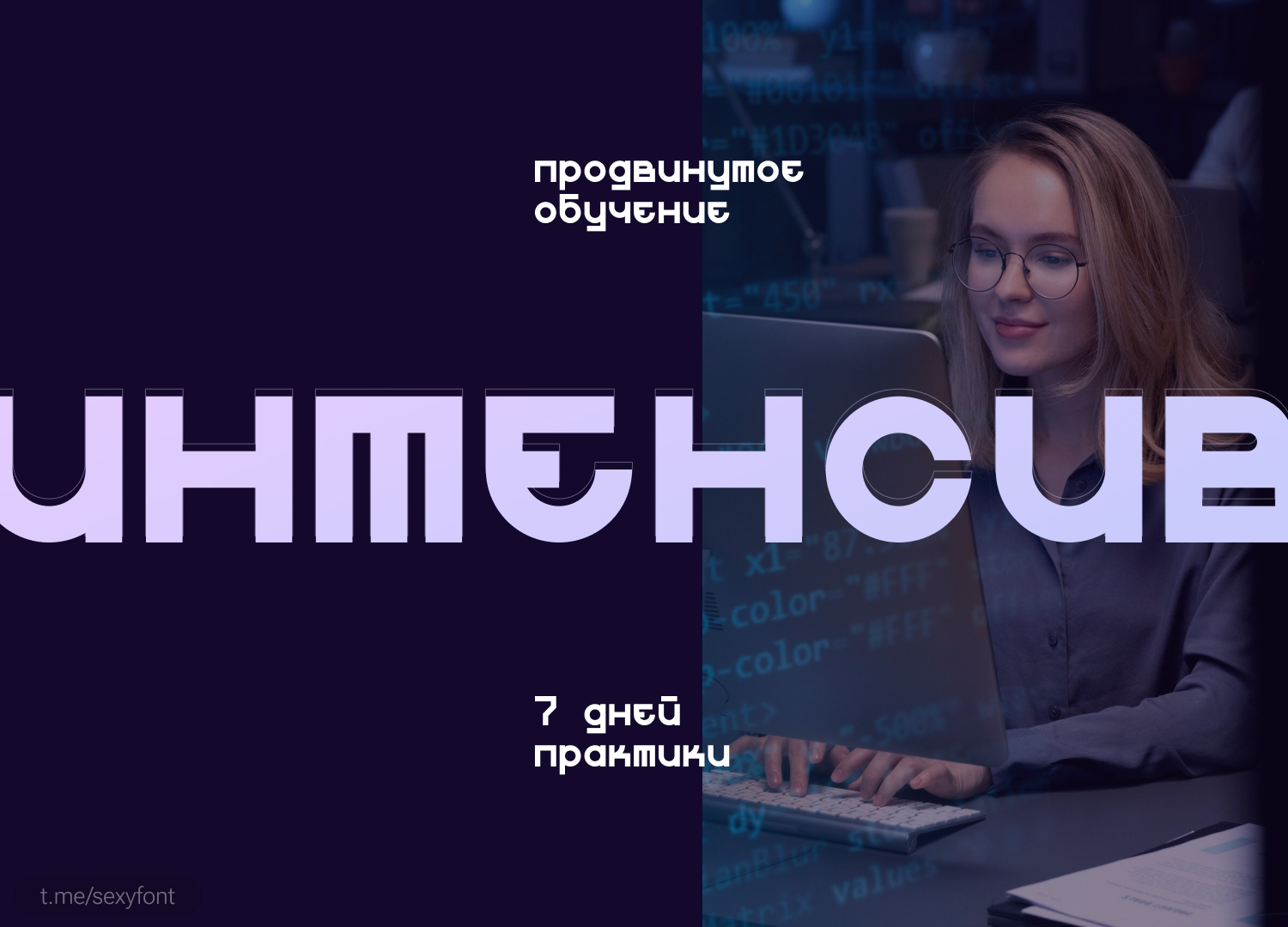
Шрифт practice
Шрифт practice. Бесплатный кириллический шрифт с острыми углами)
Автор: Алексей Атапин
Шрифт practice. Бесплатный кириллический шрифт с острыми углами)
Автор: Алексей Атапин